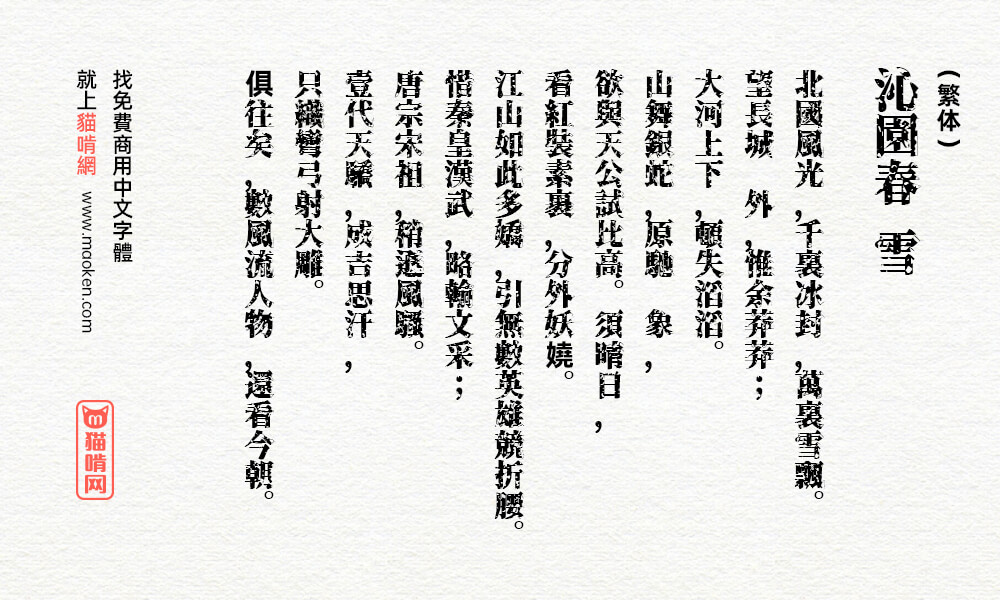
源界明朝体:以思源宋体为基础加入破坏效果魔幻霸气的免费商用字体
字体作者:浮动设计 (日本) 字体字重:1个
源界明朝这款字体是以思源宋体为基础,加入破坏效果使其最接近可读状态,可以简单理解成思源宋体的破坏版。
源界明朝在视觉上具有相当大的张力,可作为图片内的标题和大字使用,整体来说相当吸睛且颇具效果。